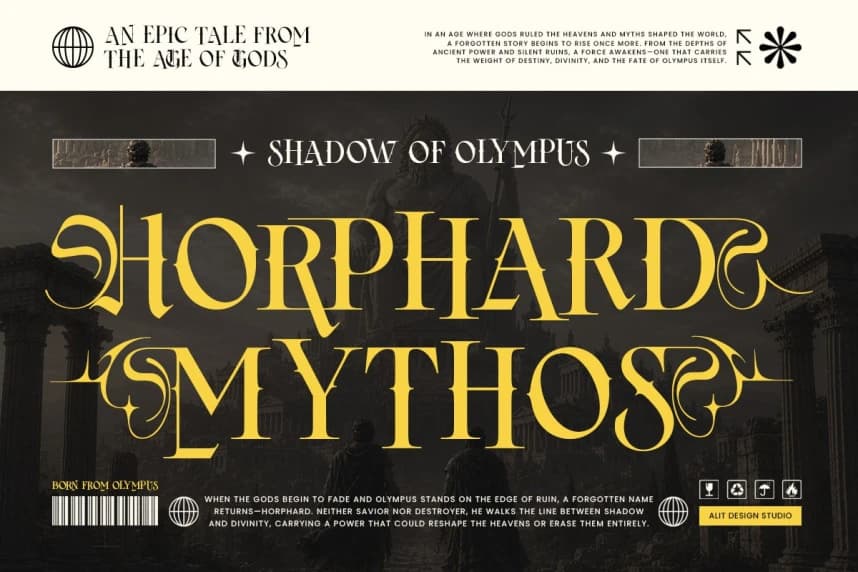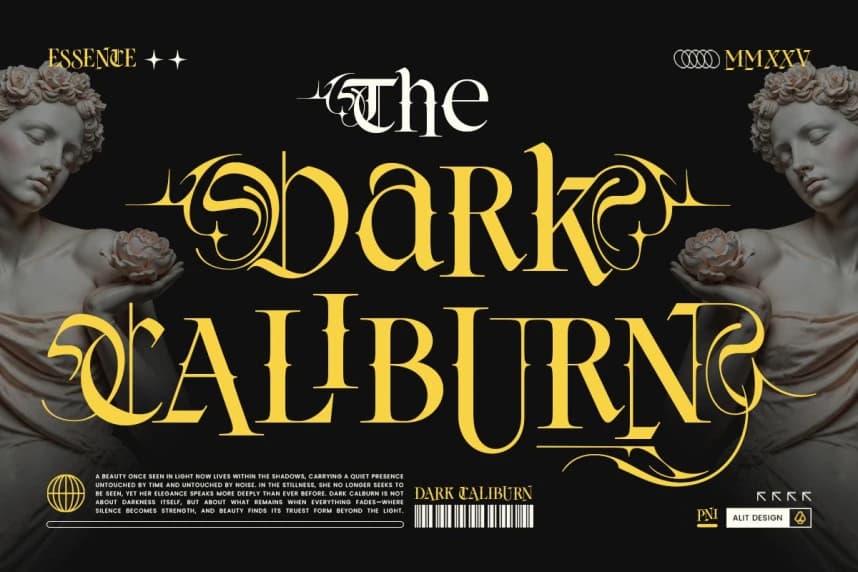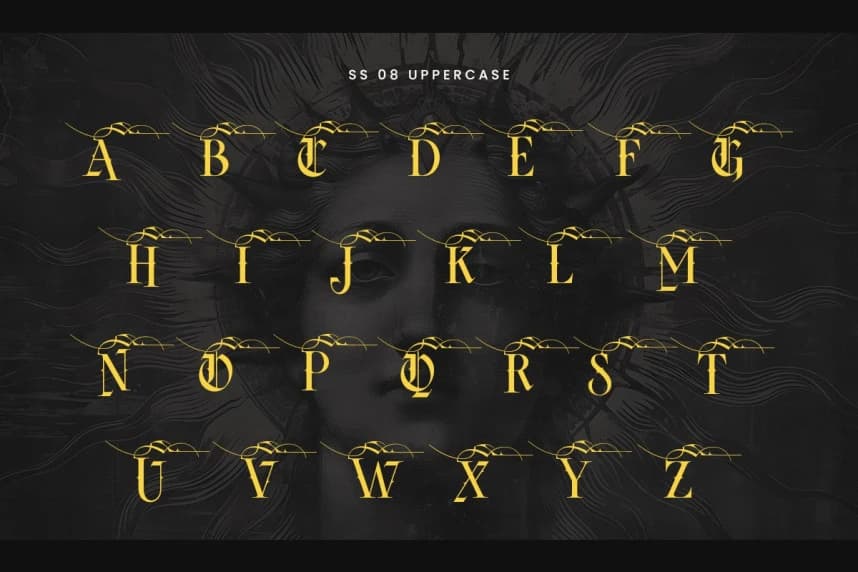
Sunsurya Font
Sunsurya Font, Alit Design Studio tarafından ustaca tasarlanmış bir blackletter yazı tipidir. Tarihi zarafet ile çağdaş ifade arasında mükemmel bir denge kurmak üzere tasarlanan Sunsurya, tipografik projelerinize cesur, dramatik ve son derece süslü bir görünüm kazandırır.
Sunsurya Font, Alit Design Studio tarafından ustalıkla tasarlanmış bir blackletter yazı tipidir. Tarihsel zarafet ile çağdaş ifade arasında mükemmel bir denge kuracak şekilde tasarlandı ve Sunsurya, tipografik projelerinize cesur, dramatik ve son derece süslü bir görünüm kazandırır.